Scrivi un nome, scegli un colore, scarica un PNG. È tutto qui, e ci vogliono una decina di secondi.
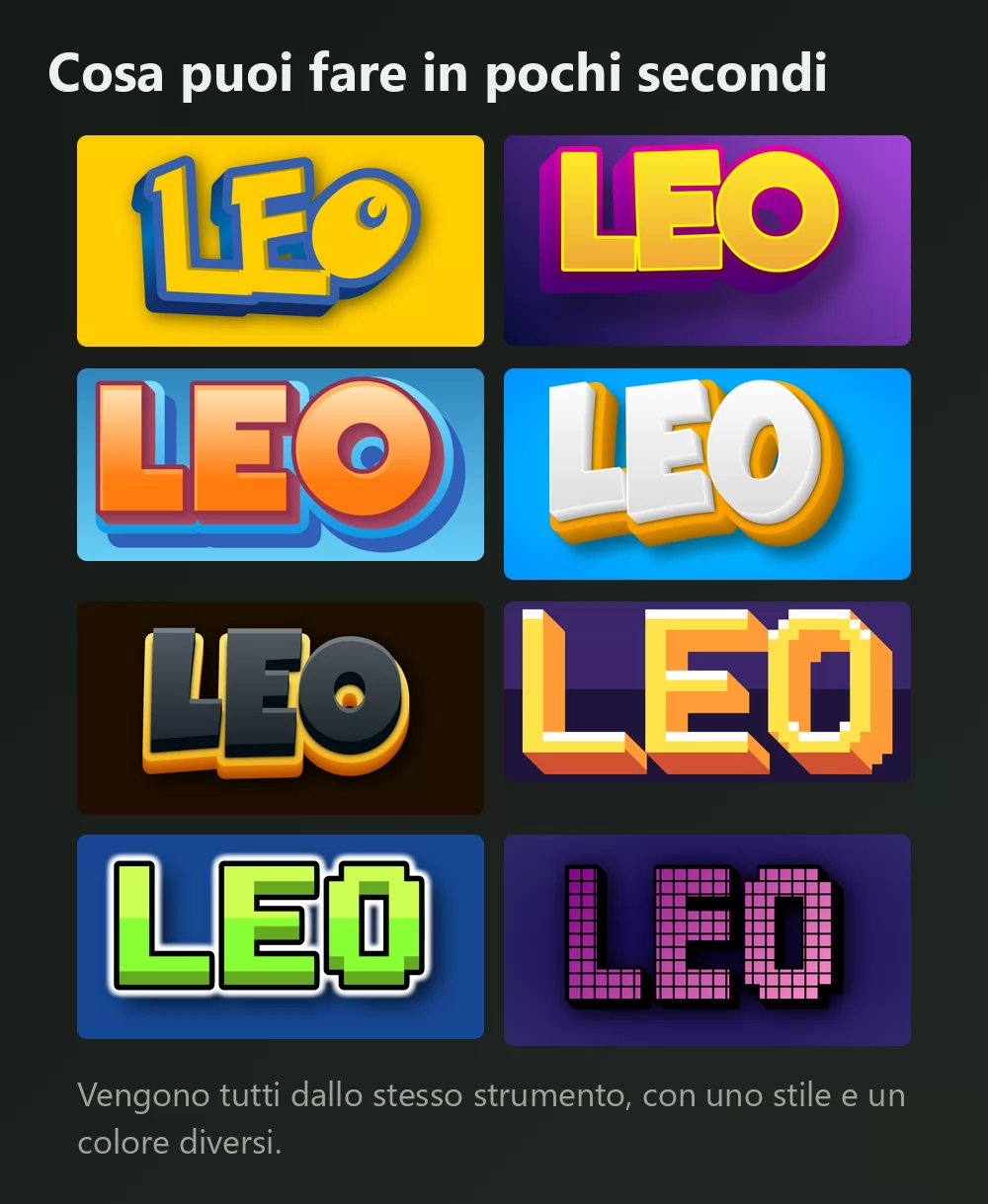
Vengono tutti dallo stesso generatore di font Pokémon, con uno stile diverso scelto dall'elenco. Niente da installare, nessun account.
Come fare un testo Pokémon
Passo 1. Scrivi il tuo nome
Apri il generatore e sostituisci il testo di esempio con quello che vuoi: un nome, una squadra, un canale, un titolo. Le lettere si ridisegnano mentre scrivi.
Passo 2. Scegli i colori
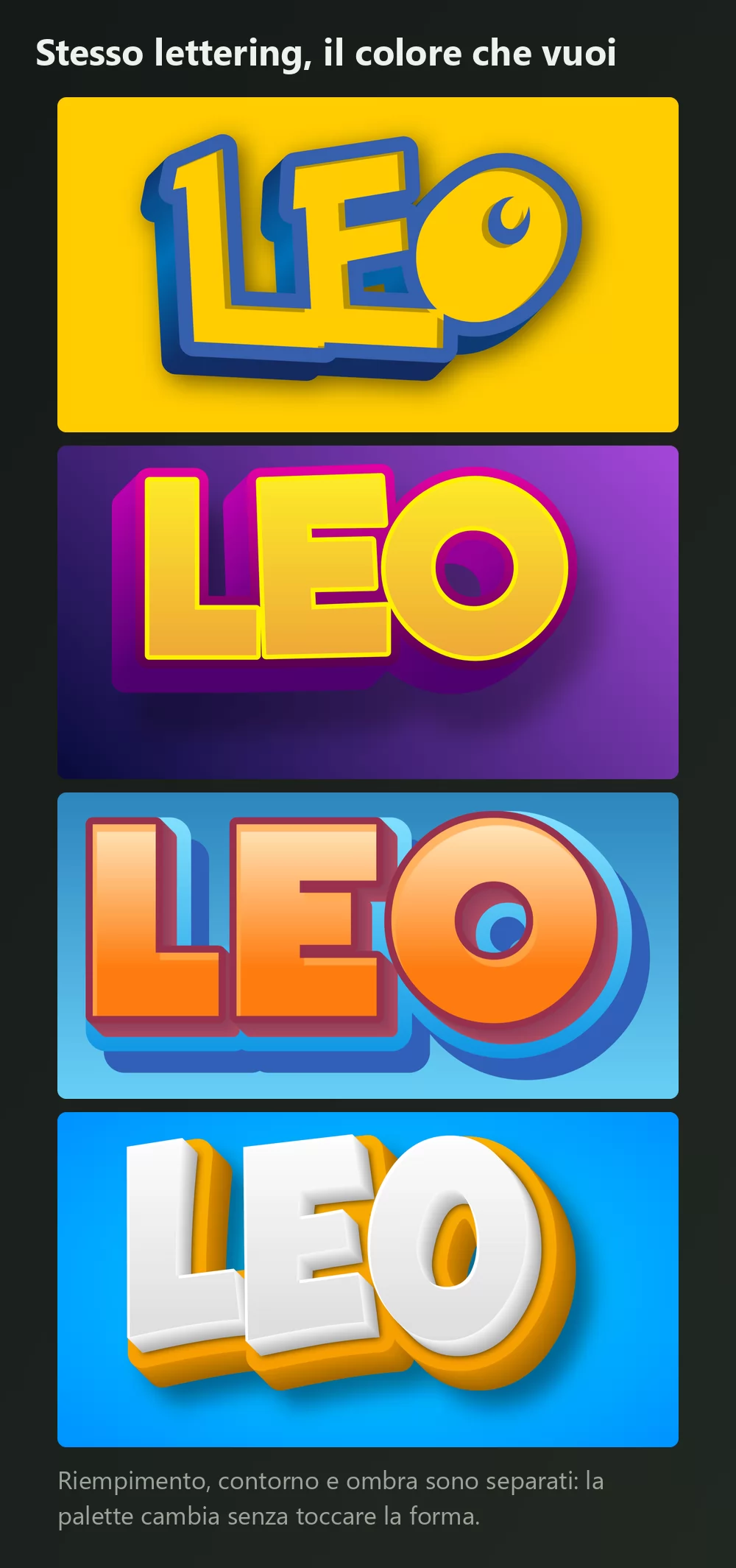
La scheda Stili ha tre pannelli, ciascuno con il suo compito:
- 3D e riempimento per il colore delle lettere: tinta unita, sfumatura o motivo.
- Contorni per il bordo, con due tipi di contorno 3D. È quel filo blu profondo a far leggere delle lettere gialle come Pokémon anziché come una semplice parola gialla.
- Ombre per le ombre esterna, interna e portata, con sfocatura e opacità.
Il giallo con contorno blu è la palette della serie, ma la forma funziona con qualsiasi accostamento.
Passo 3. Scegli il formato
Imposta il formato prima di esportare e poi non verrà ritagliato nulla. Un 16:9 per una miniatura video, un quadrato per una foto profilo, una fascia larga per un'intestazione.
Passo 4. Scaricalo
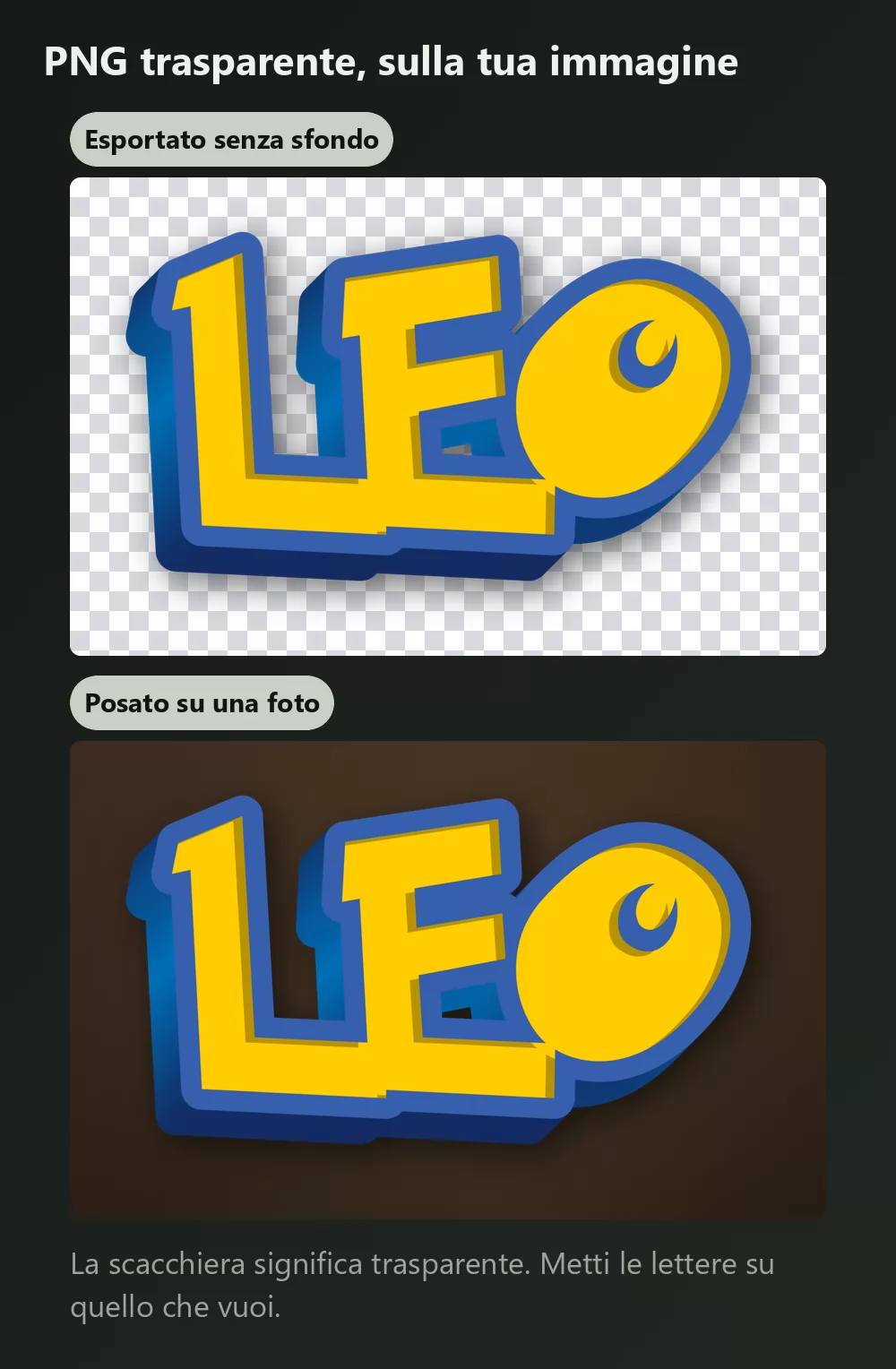
Nella scheda Scarica, prendi il PNG trasparente se conti di mettere le lettere sopra un tuo screenshot, una foto o una miniatura. È l'opzione che quasi tutti si perdono, ed è quella che fa sembrare il risultato costruito invece che incollato.
I nomi lunghi riempiono in fretta la larghezza
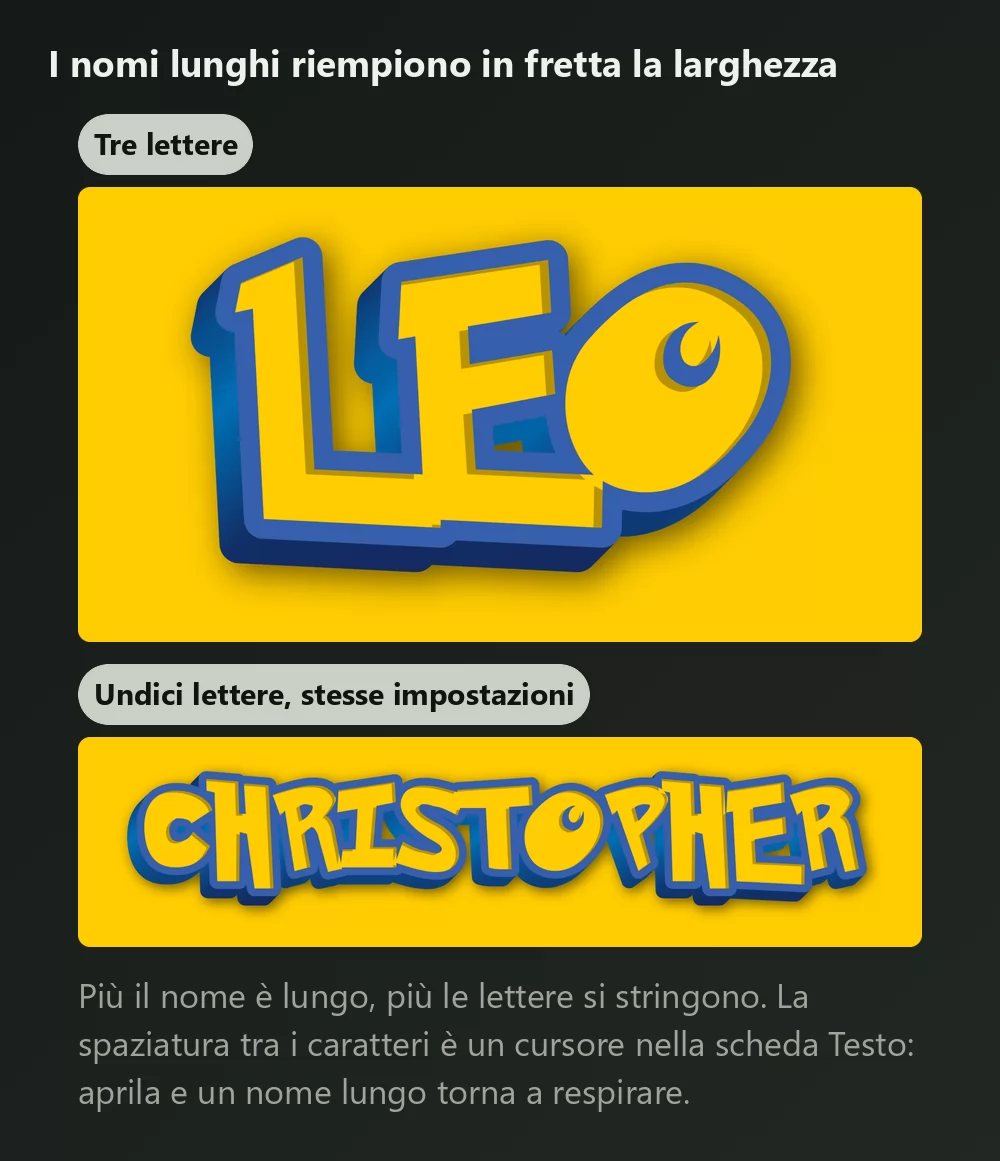
Più lettere ci sono, più si stringono. La spaziatura tra i caratteri è un cursore nella scheda Testo: aprila un po' e un nome lungo smette di stare stretto. Nella stessa scheda ci sono zoom, interlinea, curva e rotazione.
Curvare il testo
Il cursore della curva è ciò che dà slancio a un titolo, ed è la differenza tra una parola piatta e qualcosa che sembra progettato. Ne serve poca: oltre un certo punto le lettere si aprono a ventaglio e il nome diventa difficile da leggere.
Stile del logo o stile dei giochi?
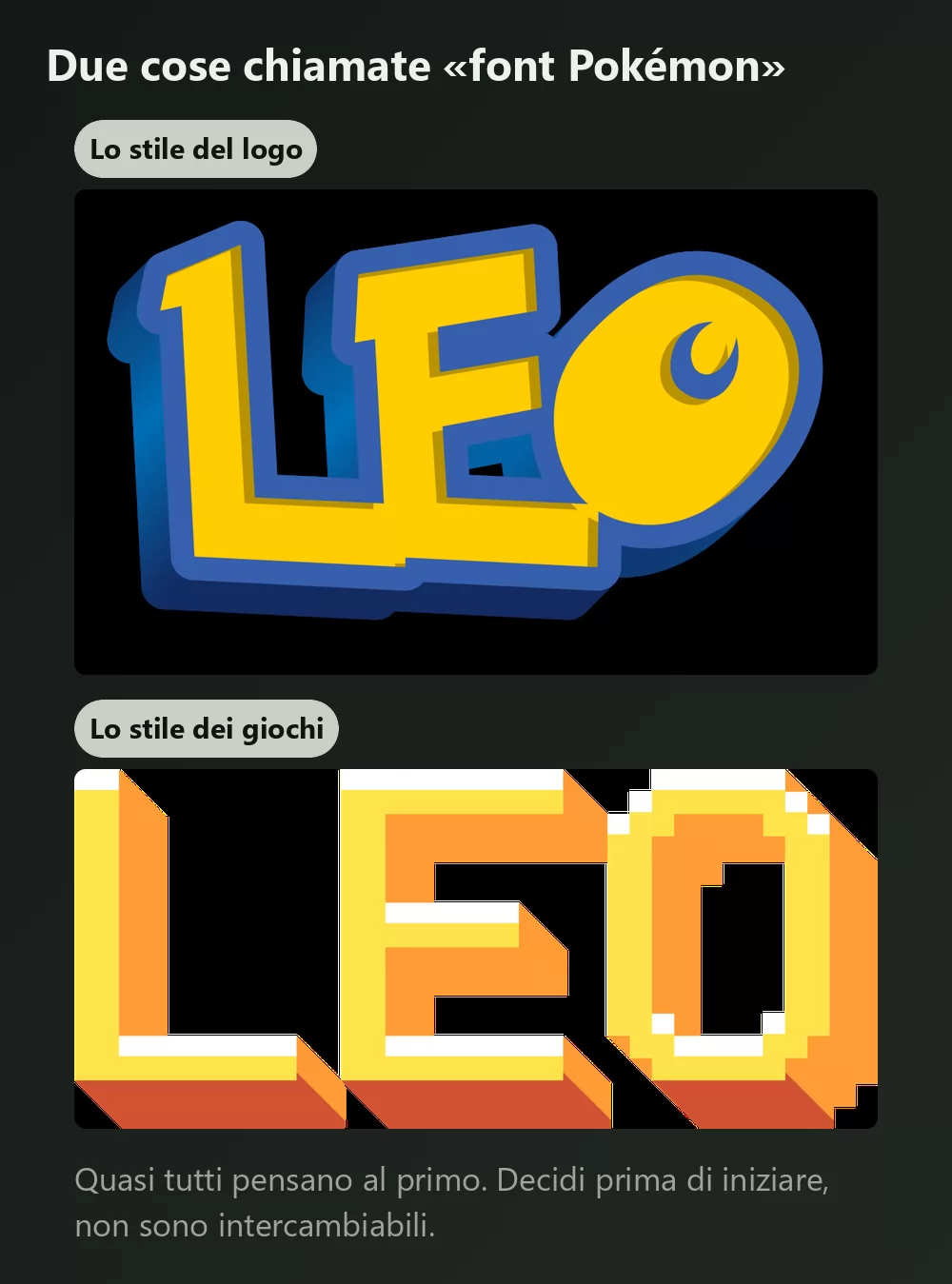
Due cose diverse si chiamano «il font di Pokémon». Quasi tutti pensano alla prima.
Lo stile del logo sono le lettere spesse e arrotondate con contorno marcato e un po' di rilievo: è quello che dà il generatore qui sopra.
Lo stile dei giochi sono le piccole lettere a pixel delle console portatili. Se cerchi quelle, un effetto di testo a pixel 8 bit ti ci porta.
Il font si chiama Pokemon Solid
Se preferisci installare un font e comporre il testo da solo, è questo il nome da cercare. La ricostruzione dei fan su DaFont, chiamata semplicemente «Pokemon», ha superato i sette milioni di download e arriva in due file:
- Pokemon Solid è la versione piena, quella che vuoi per un titolo.
- Pokemon Hollow è solo il contorno, per le dimensioni grandi che riempi tu.
Una cosa da mettere in conto: il font dà le forme delle lettere e nient'altro. Il contorno blu, il riempimento, il rilievo e l'ombra sono effetti da costruire dopo, cioè esattamente il lavoro che il generatore fa per te.
Altri font Pokémon da conoscere
- Pokemon GB ricostruisce il piccolo carattere bitmap dei giochi Game Boy. Giusto per una finta finestra di dialogo, sbagliato per un titolo.
- Pocket Monk è un'altra lettura del lettering del logo, utile se Pokemon Solid non convince.
- Pokemon Pixel Font è squadrato con diagonali a gradini, più vicino a uno schermo da sala giochi che alla serie.
Sono tutte ricostruzioni dei fan. Il lettering ufficiale è stato disegnato per il marchio e non è mai stato pubblicato come font.
Come fare un testo Pokémon in Canva
Canva non ha un font Pokémon nella sua libreria, e sul piano gratuito non se ne può installare uno. La via d'uscita è costruire il lettering come PNG trasparente e caricarlo: entra direttamente in un progetto Canva e resta nitido.
Come fare un testo Pokémon in Photoshop
Installa Pokemon Solid, scrivi il testo, poi ricostruisci il trattamento con gli stili di livello:
- Traccia, impostata su Esterno, in un blu profondo, piuttosto spessa.
- Sovrapposizione sfumatura o un riempimento pieno giallo per le lettere.
- Ombra esterna, spostata in basso e leggermente a destra, con opacità bassa.
Così ci si avvicina. Il rilievo del logo vero viene da un livello duplicato e spostato dietro al primo, difficile da tenere regolare su tutte le lettere.
Come fare un testo Pokémon in Word
Installa il font, scrivi il testo, poi usa gli effetti di testo per contorno e ombra. Gli effetti di Word sono molto più grossolani di quelli di un editor di immagini: per qualsiasi cosa da stampare o pubblicare, un PNG esportato verrà meglio di quello che Word sa costruire.
Sul telefono
Non puoi installare un font e usarlo nella maggior parte delle app, né su iOS né su Android. Il generatore gira nel browser del telefono, quindi la via pratica è fare il PNG sul telefono, salvarlo nella galleria e aggiungerlo nell'app che stavi usando.
Come ottengo uno sfondo trasparente? Scegli il PNG trasparente nella scheda Scarica, poi metti le lettere sopra la tua immagine.
Perché il mio testo non somiglia al logo anche con il font giusto? Perché un font è solo la forma delle lettere. Il contorno blu, il rilievo e l'ombra sono effetti applicati sopra.